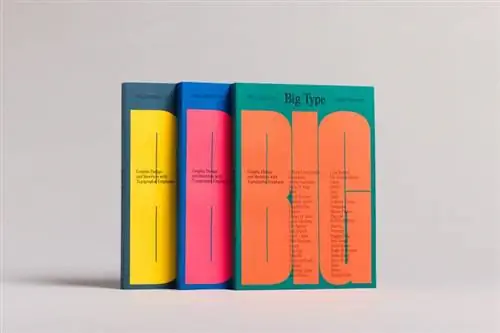
Если подумать о тенденциях типографики последних лет, то одна из них особенно выделяется. Крупный жирный шрифт можно увидеть повсюду, от рекламных щитов до веб-сайтов, от моушн-дизайна до кинофильмов. Так что приятно видеть новую книгу от Counterprint, посвященную именно этой теме.
Как и следовало ожидать из названия, Big Type исследует графический дизайн и работу с идентификацией, где упор делается на крупный шрифт. (Или это должен быть БОЛЬШОЙ ТИП?). И это действительно своевременный релиз.
Визуальный ландшафт, в котором появляется творческая работа, становится все более загроможденным, а цифровой мир настолько огромен, что сделать свою работу видимой становится все труднее и труднее. Крупный шрифт - это один из инструментов в вашем арсенале, и хотя его никогда не следует использовать бездумно, он может стать отличным способом добиться того, чтобы ваш дизайнерский голос был услышан.
Чтобы увидеть, как это делается, просто ознакомьтесь с работами, представленными в этой книге. Все это блестящие примеры увлекательного направления в графическом дизайне, созданного столкновением технологий, типографики и трендов и создающего сегодня новые захватывающие результаты.
Книга разделена на разделы, посвященные масштабированию, повторению, обрезке, надписям, искажению и взаимодействию. Он наполнен сногсшибательными изображениями от лучших графических дизайнеров мира, а также содержит интервью с агентствами и поучительные описания проектов, чтобы добавить контекст к визуальным эффектам.
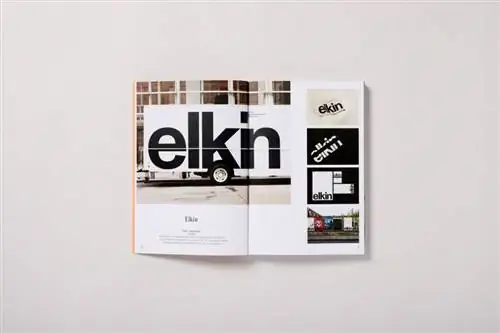
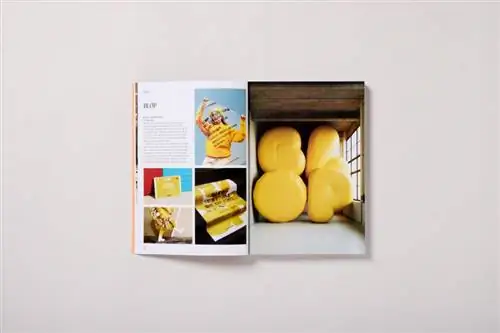
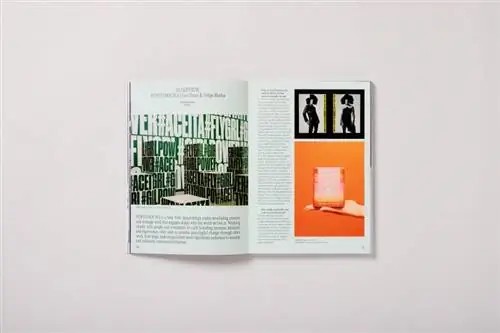
Что вдохновило на создание книги?
Книга началась как шутка. [Соучредитель Counterprint Селин Летерм] и я работали в брендинговых агентствах в Лондоне, прежде чем открыть собственную студию и перейти к публикации позже в нашей карьере. Всякий раз, когда мы работали над айдентикой, клиенту часто предлагался вариант «крупного шрифта». Я думаю, что «крупный шрифт» - это сокращение для определенного стиля дизайна, который дизайнеры могут сразу же вспомнить.
Как и многих, меня всегда привлекали подобные проекты, поскольку они привлекают внимание и воспевают красоту шрифта. Первоначальная реакция на книгу, ее название и содержание была такой теплой - не похожей ни на что, с чем мы сталкивались раньше. Кажется, дизайнерам что-то мешает создавать и просматривать такие работы.
Глядя на проекты, можно сказать, что графический дизайн сейчас на улицах как никогда раньше. Как вы думаете, что изменилось?
Я думаю, что платформы, с помощью которых современный бренд может выразить себя, расширились с развитием технологий. Технологии стали основой всей нашей жизни. В то время как несколько лет назад деятельность графического дизайнера в основном ограничивалась созданием плакатов, рекламы, упаковки, вывесок и т. д., работа современного дизайнера теперь расширилась и охватывает практически все области репрезентации и дизайна.
На улице, в частности, бумага была частично заменена цифровыми экранами, что расширило рекламное пространство от статического до анимированного. Между тем, шрифты теперь также можно настраивать и анимировать. Все это привело, с точки зрения бренда, к визуальной идентичности, которая превратилась из статической в динамическую, с гораздо более богатыми возможностями коммуникации, чем это было ранее.
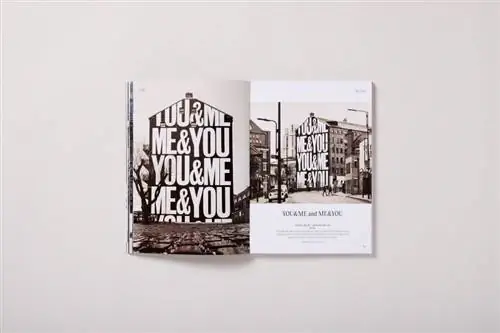
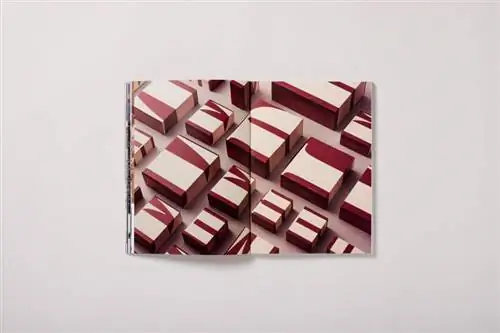
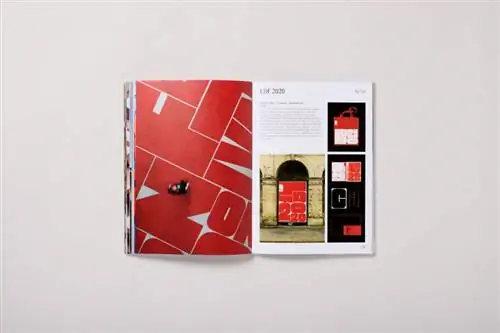
Как вы выбирали проекты для книги и какие из них вам больше всего нравятся?
Все проекты в книге были выбраны за их силу и убедительность, которые должны были прорваться через визуальный шум, с которым мы сталкиваемся каждый день, и передать сообщение, вызвать ответ или представить призыв к действию.
Трудно выделить один или два проекта, но всегда есть какие-то личные фавориты. Мне нравится абсолютная брутальность логотипа Order и фирменного стиля Elkin, независимой студии видеопроизводства. Заказ разработал новое прозвище для компании, чтобы быстро идентифицировать бренд среди часто похожих производственных сред.
Работа Futura для BLOP, фестиваля искусства, дизайна и культуры, также является фаворитом. BLOP родился из идеи разрушить «пузырь», который изолировал нас всех во время блокировки Covid. Основываясь на этой концепции, Futura разработала брендинг для всего фестиваля с изображениями воздушных шаров, надувающихся до предела.
Что, по вашему мнению, люди получат от этой книги?
Я надеюсь, что это вдохновит людей иногда оставлять свои запреты позади при проектировании и заходить немного дальше, чем им удобно. Я надеюсь, что со всеми нашими книгами люди увидят, что дизайн может быть творческим, веселым, страстным, интеллектуальным и полезным занятием - как для целевой аудитории, так и для дизайнера, выполняющего работу.